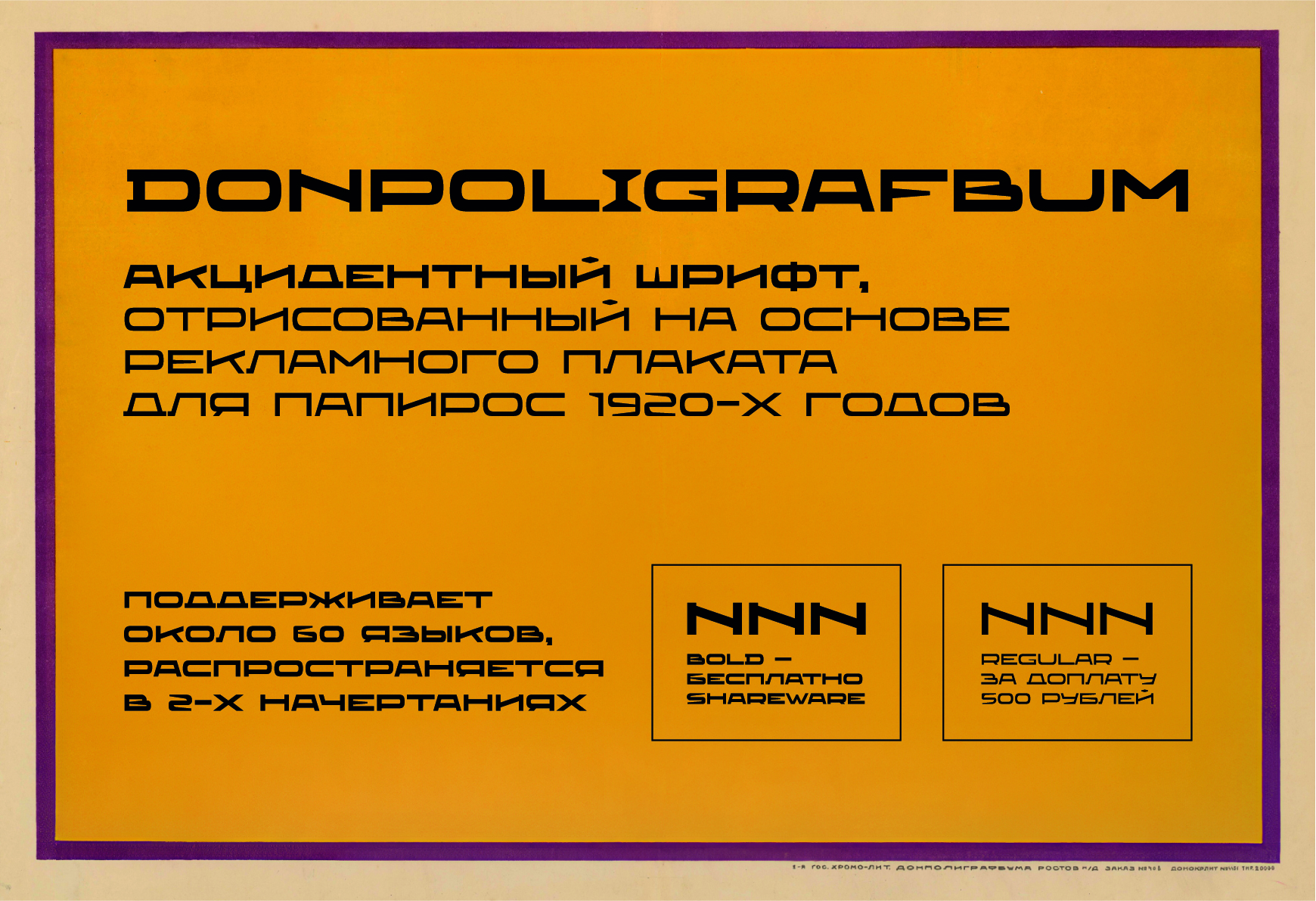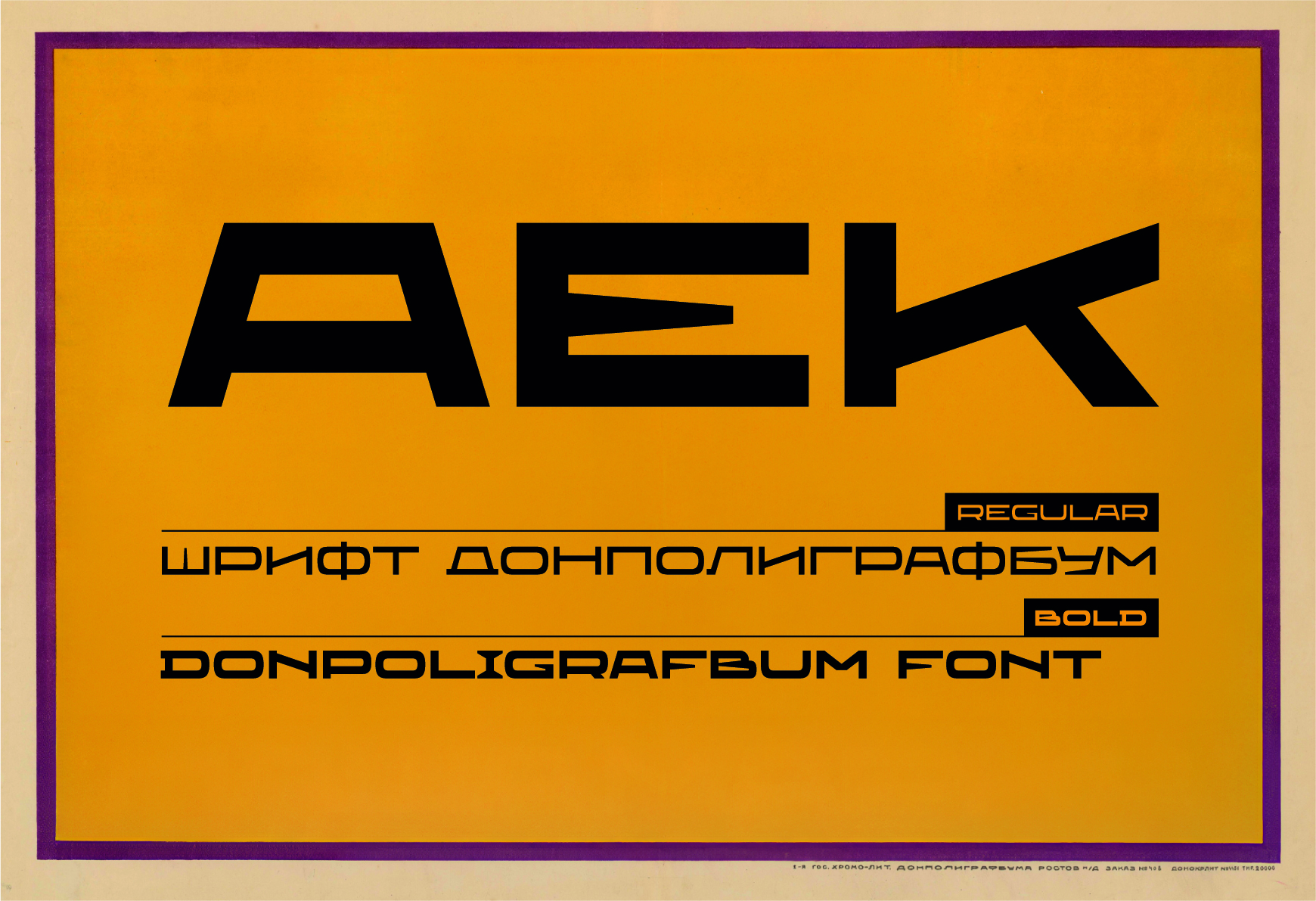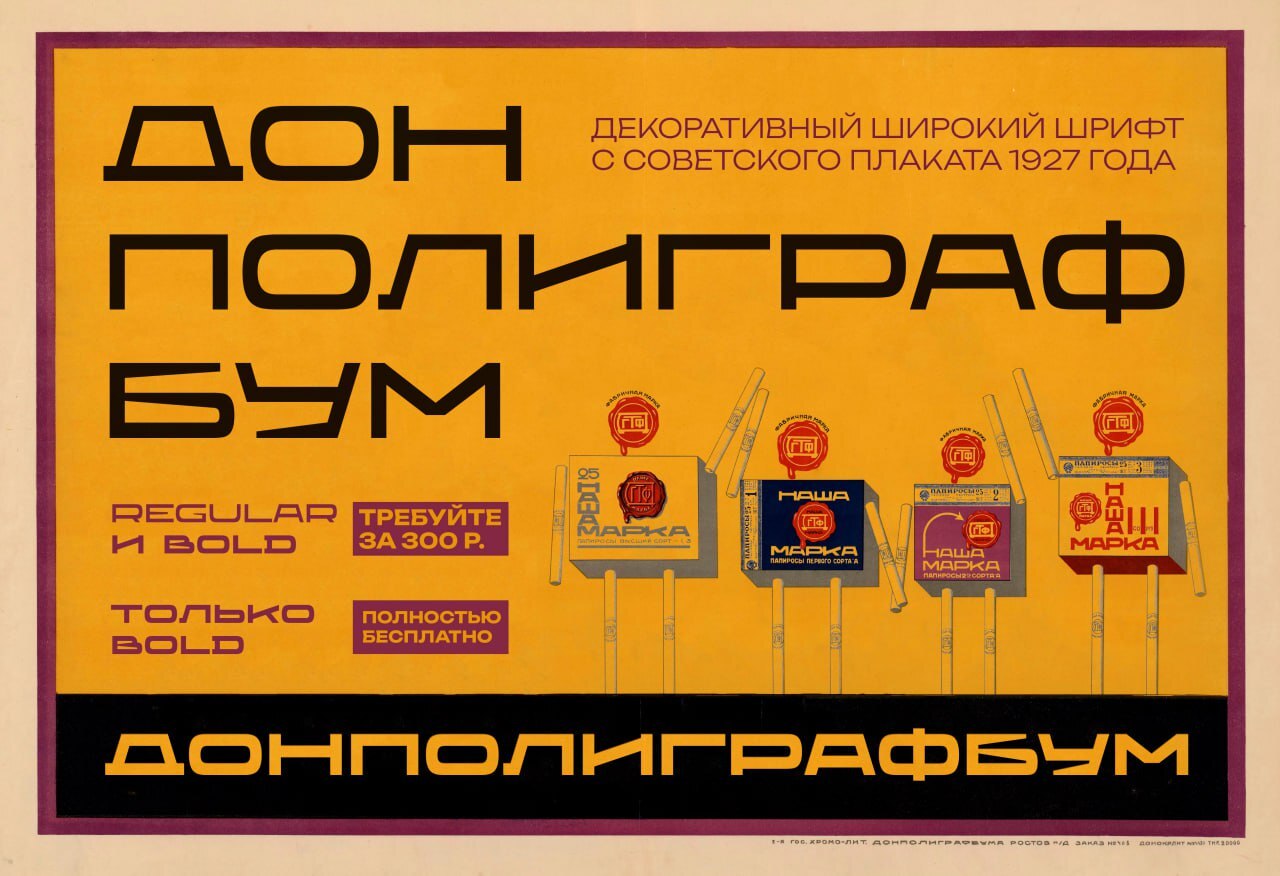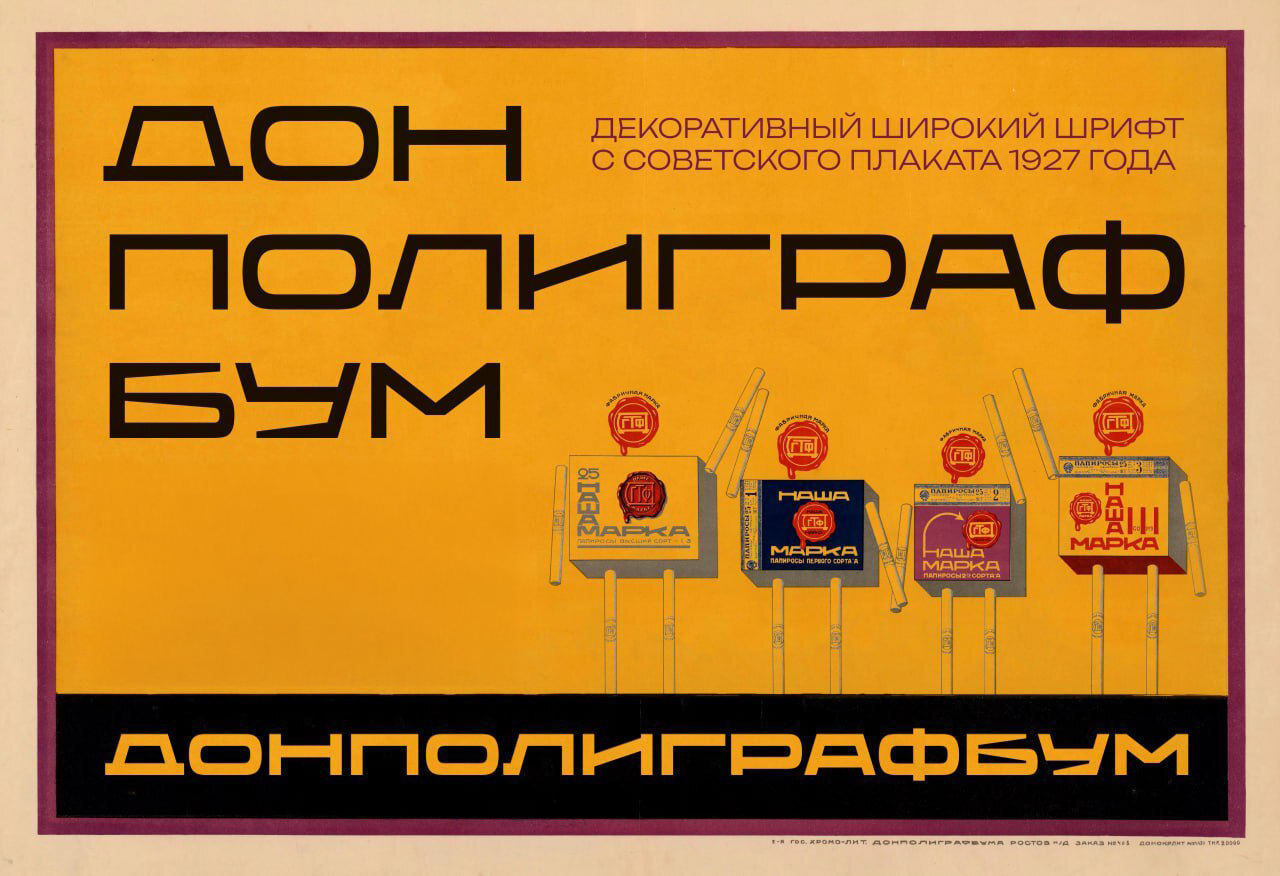
Шрифт Донполиграфбум
Donpoligrafbum — широкий акцидентный гротеск, сделанный по рекламному плакату папирос «Наша марка» конца двадцатых годов. Массивные штрихи и плотный ритм роднят его с конструктивистской графикой того времени, при этом рисунок остаётся аккуратным и пригодным для современной вёрстки. Полнее всего он раскрывается в крупных размерах: заголовки, обложки, вывески, выставочная и музыкальная графика, айдентика с оглядкой на советский модернизм. В комплекте — полная версия STAR и лицензия.
Designer Sasha Pavljenko